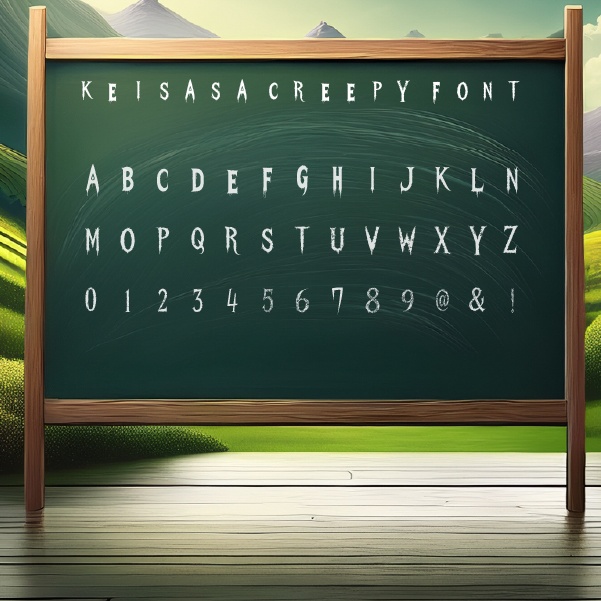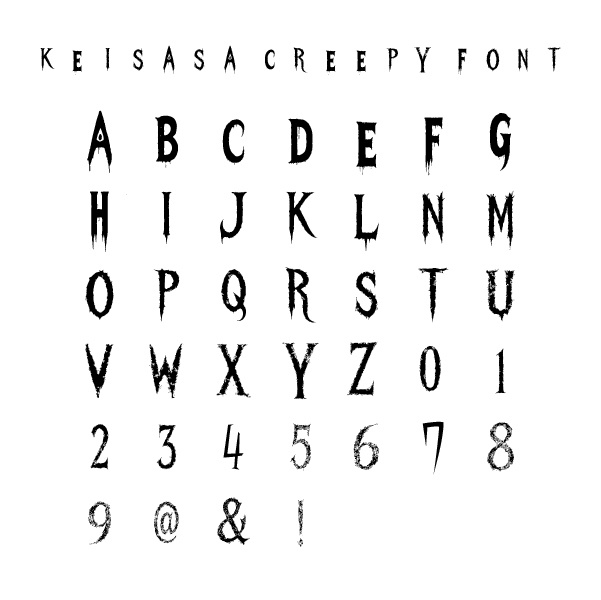
【商用可】Keisasa creepy font|ホラー・スプラッター風フォント(大文字のみ)
Keisasa Creepy Font(ケイササ クリーピー フォント)は、 尖ったエッジとにじむようなディテールが特徴のホラーテイストな英字フォントです。 スプラッター、ミステリー、ダークファンタジー、ゲーム、ハロウィンなどの作品にぴったり。 ✅ フォント内容 大文字英字のみ対応(小文字は含まれません) 数字・記号(@ & ! など)収録 TTF形式(TrueType Font) 商用利用可(※利用規約をご確認ください) ⚠️ 利用規約(抜粋) 商用利用可能 再配布・再販売は禁止 著作権は保持しています Title Keisasa Creepy Font – Bold, Spiky, and Perfect for Horror Designs Description Keisasa Creepy is a bold, high-impact display font designed with horror and dark fantasy in mind. The jagged, dripping shapes bring an eerie and thrilling energy to posters, Halloween projects, game titles, and more. Uppercase letters only Includes numerals and symbols (@ & !) TTF format Commercial use allowed (see license image for details) Redistribution and resale are not permitted